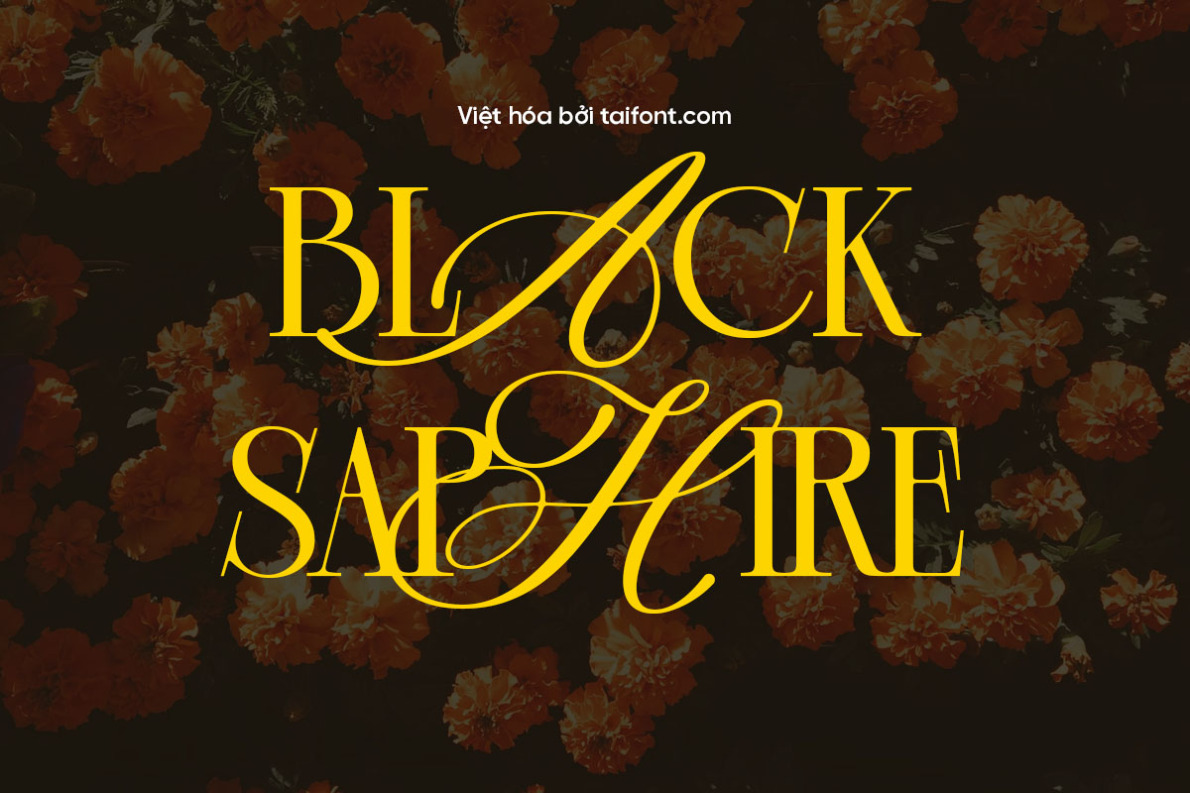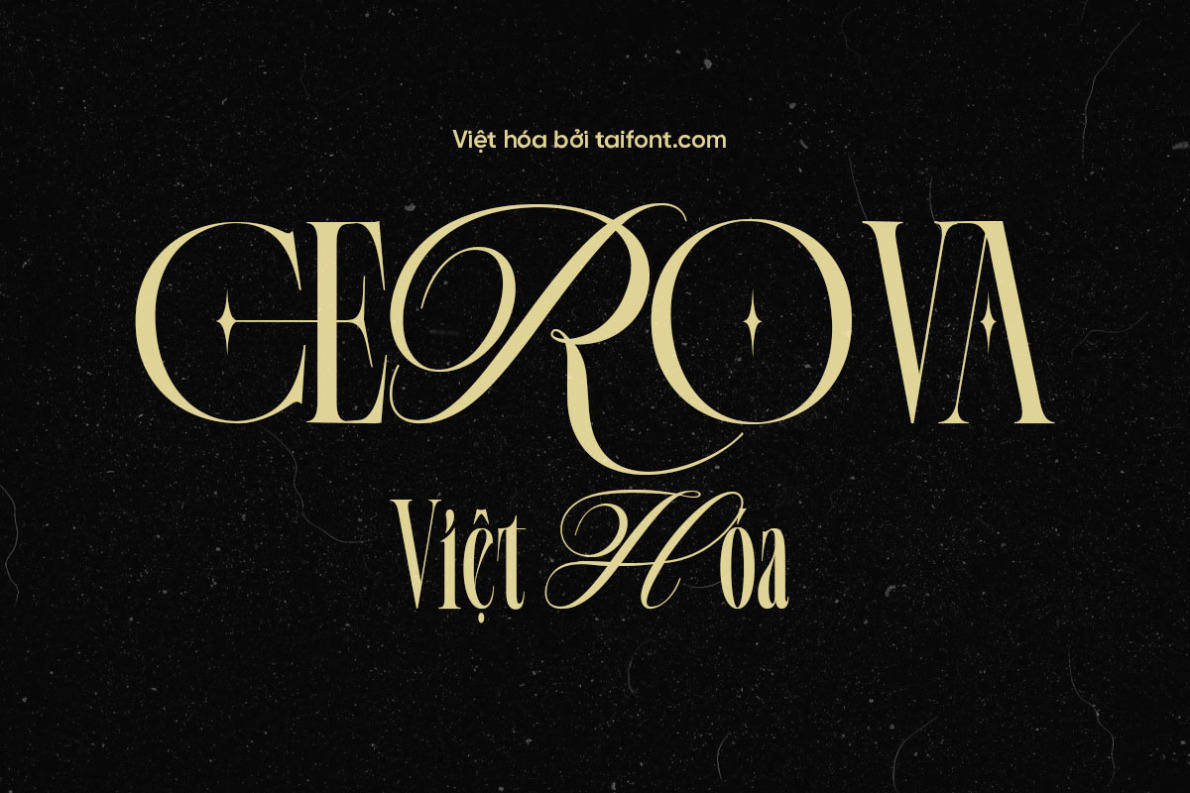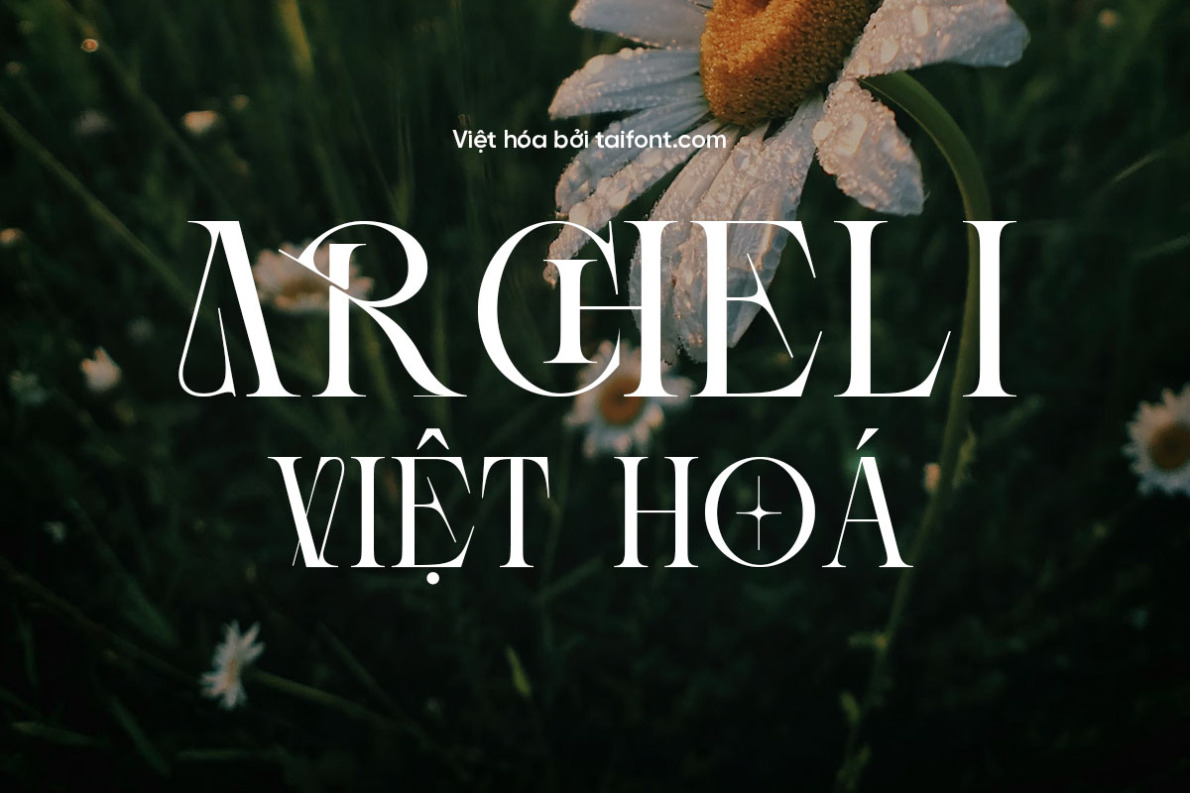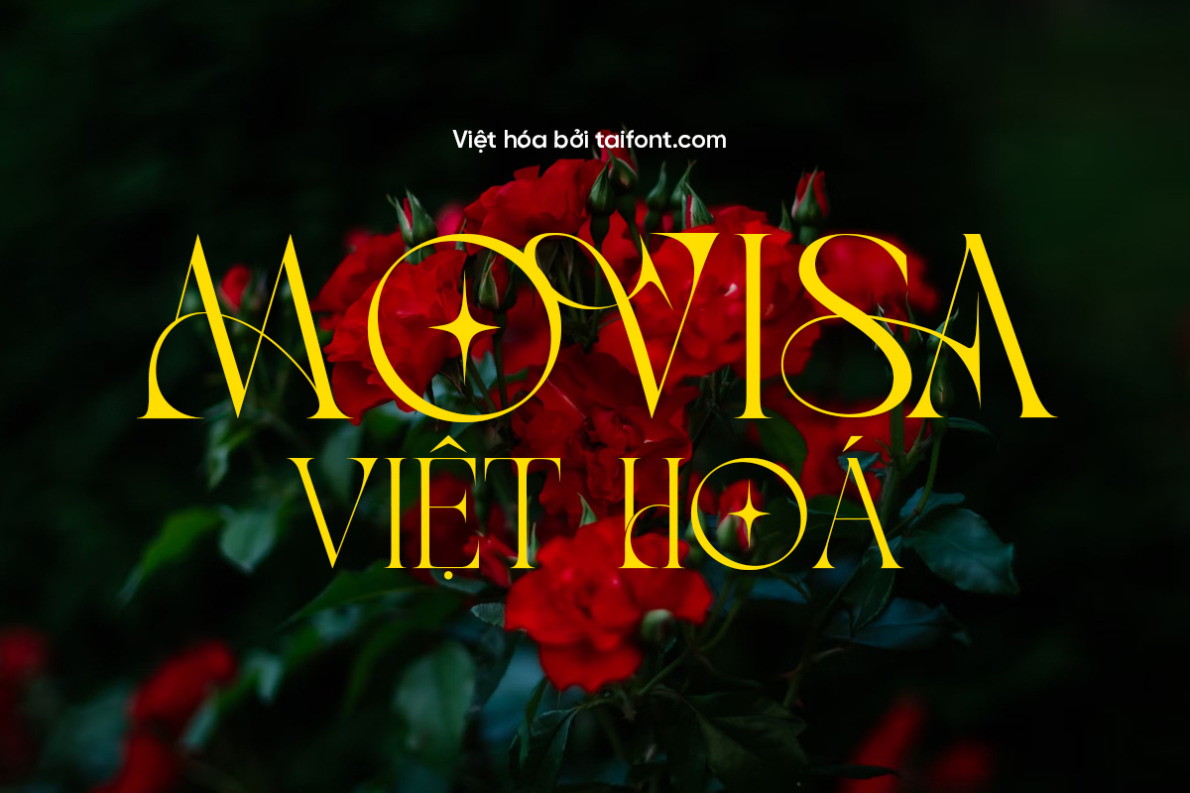
Tải Ngay! Top Font Việt Hóa Đẹp Cho MV Ca Nhạc: Nâng Tầm Cảm Xúc Âm Nhạc
Trong thế giới của âm nhạc và hình ảnh, một MV ca nhạc không chỉ là sự kết hợp giữa giai điệu và giọng hát, mà còn là một tác phẩm nghệ thuật thị giác tổng thể. Và trong bức tranh đó, font chữ đóng vai trò cực kỳ quan trọng, đặc biệt khi bạn muốn truyền tải lời bài hát (lyrics) hay tạo dấu ấn thương hiệu cho nghệ sĩ. Một font chữ phù hợp có thể thổi hồn vào từng câu hát, nhấn nhá cảm xúc, và nâng tầm trải nghiệm của người xem.
Nếu bạn đang ấp ủ dự án làm MV ca nhạc, lyrics video, hay bất kỳ sản phẩm đồ họa nào liên quan đến âm nhạc, thì việc tìm kiếm những bộ font Việt hóa đẹp và ấn tượng là điều không thể thiếu. Font chữ không chỉ cần rõ ràng, dễ đọc mà còn phải mang một phong cách riêng, hòa quyện với tinh thần của bài hát – dù là một bản ballad nhẹ nhàng, một ca khúc pop sôi động, hay một tác phẩm rock mạnh mẽ.
2 Font Việt hóa TF Movisa – MV ca nhạc, đám cưới
TF Movisa Việt hóa là một font chữ có chân (serif) nổi bật với vẻ đẹp sang trọng, tinh tế và đầy quyến rũ. Font này được thiết kế với những đường nét thanh lịch, mềm mại nhưng vẫn giữ được sự rõ ràng và chuyên nghiệp, toát lên phong thái quý phái và đẳng cấp, lý tưởng để tạo nên sự độc đáo cho mọi thiết kế.
Font Việt hóa TF Archeli – Font MV Âm nhạc, tạp chí
TF Archeli Việt hóa là một font chữ có chân (serif) nổi bật với thiết kế đặc sắc, tinh tế và đầy cuốn hút, lý tưởng để tạo nên sự sang trọng và cá tính riêng cho mọi thiết kế. Font này toát lên vẻ đẹp nghệ thuật, hoài niệm nhưng vẫn rất hiện đại, phù hợp để thu hút mọi ánh nhìn và tạo ấn tượng mạnh mẽ.
Font Việt hóa TF Black Saphire – Font MV ca nhạc, tạp chí
TF Black Saphire Việt hóa là một font chữ vô cùng độc đáo và sáng tạo, nổi bật với sự kết hợp đầy thú vị giữa hai kiểu thiết kế hoàn toàn khác biệt giữa chữ viết hoa và chữ thường
Font Việt hóa TF Cerova – Nhiều Glyphs, font cho MV ca nhạc
TF Cerova Việt hóa là một font chữ có chân (serif) nổi bật với vẻ đẹp tinh tế và đẳng cấp, cùng với kho Glyphs (ký tự đặc biệt) phong phú. Được thiết kế tỉ mỉ, Cerova kết hợp hài hòa giữa nét cổ điển và sự hiện đại, mang đến sự sang trọng và khả năng tùy biến cao, giúp bạn tạo ra những thiết kế độc đáo.
Font Việt hóa TF Crown Emperial – Font cho MV ca nhạc
TF Crown Imperial Việt hóa là một font chữ có chân (serif) được mệnh danh là đỉnh cao của vẻ đẹp và sự tinh tế. Với những đường nét được thiết kế vô cùng sang trọng, uyển chuyển và đầy quý phái, font này toát lên sự đẳng cấp vượt trội, mang đến cảm giác vương giả và thanh lịch.